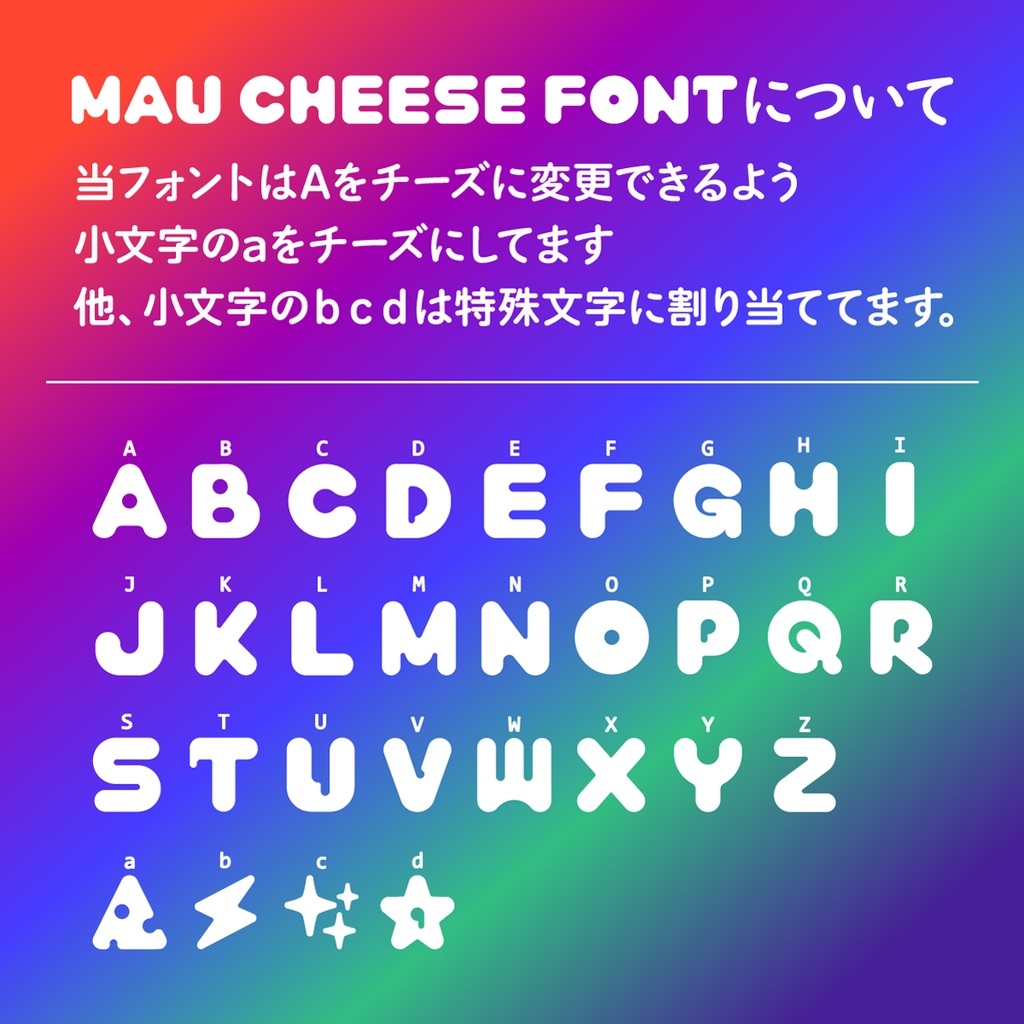
MAU CHEESE FONT
溶けたチーズのようなかわいいフォントです。 オススメのPhotoshopの文字設定は カーニング設定「オプティカル」+文字トラッキング設定「-25」です。 FONTTYPE:OpenType ----------------------------------------------------------- 「MAU CHEESE」フォントは 仕様変更などのバージョンアップすることがあります。 ----------------------------------------------------------- このフォントはAdobe Illustrator2022と 武蔵システム(http://opentype.jp)のOTEditを使って作成しております。 ----------------------------------------------------------- ■ 免責事項 ■ 本フォントデータの使用に関連して、購入者の直接、及び間接的に生ずる一切の損害および第三者からなされる請求について一切責任を負担しません。 ■ 禁止事項 ■ サーバー等にアップロードして送信可能とする目的の使用は出来ません。 データの改変、販売、頒布、バックアップ目的以外のコピーは許可しておりません。 データを使用して作成した成果物の知的財産権の登録を行うことは許可されていません。